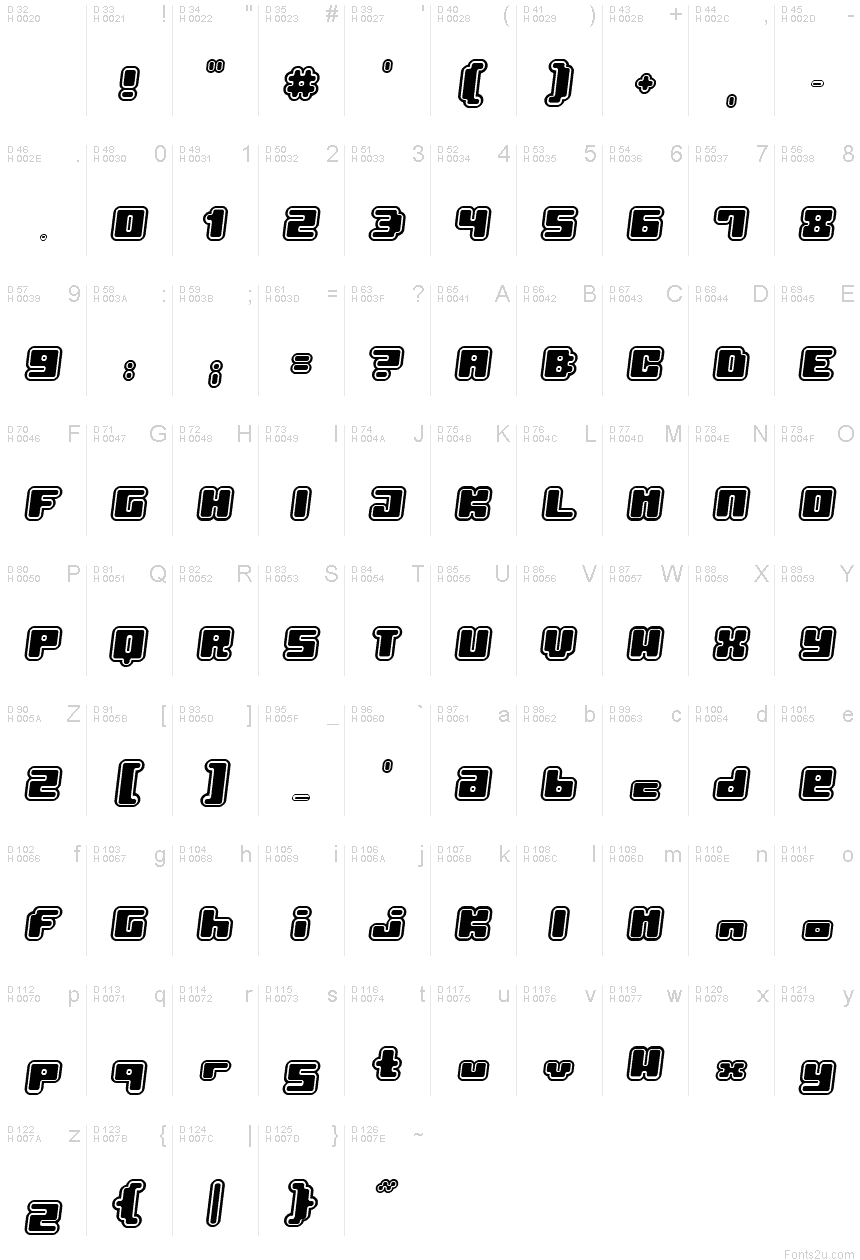
Pormask Ytterhud od TarmSaft font factory to darmowy, futurystyczny font typu display w stylu groovy, wyróżniający się miękkimi, „napompowanymi” konturami i wyrazistą podwójną obwódką. Litery wyglądają jak odlane, a nie narysowane – mają zaokrąglone rogi, głębokie cięcia i charakterystyczne dla sci-fi lat 90. wibracje, dzięki czemu alfabet jest żywy i skoczny, a nie surowy.
To naturalny wybór do plakatów, ulotek klubowych, tytułów gier, okładek i szkiców logo, gdzie to same litery budują klimat. Jako darmowy krój, sprawdza się szczególnie w krótkich nagłówkach i na planszach tytułowych, ponieważ grube kontury i kompaktowe wnętrza nadają nawet pojedynczym słowom mocny, techniczny charakter w stylu zabawek.